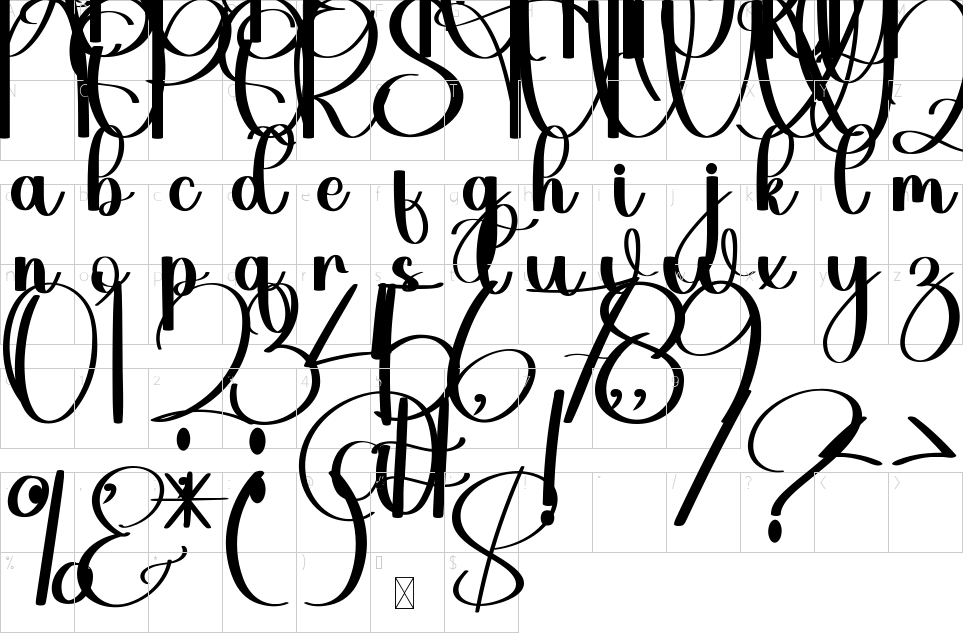
Deary Samantha Font – Download Grátis
Descubra a delicadeza e a elegância das Letras Deary Samantha, uma fonte gratuita perfeita para designers digitais e amantes do bom gosto. Criada pelo InermediaSTUDIO, esta fonte foi projetada com um toque moderno que se destaca em qualquer projeto de layout gráfico. Com seus traços suaves e elegantes, Deary Samantha é uma escolha perfeita para textos legíveis e atraentes, seja em títulos ou subtítulo. Se você busca fontes gratuitas de alta qualidade, não hesite em dar uma olhada nesta fonte apresentando um design refinado e moderno. Com seu download fácil e versátil para uso em Windows e Mac, Deary Samantha se torna a escolha ideal para quem está sempre buscando novas possibilidades no seu trabalho de arte digital.